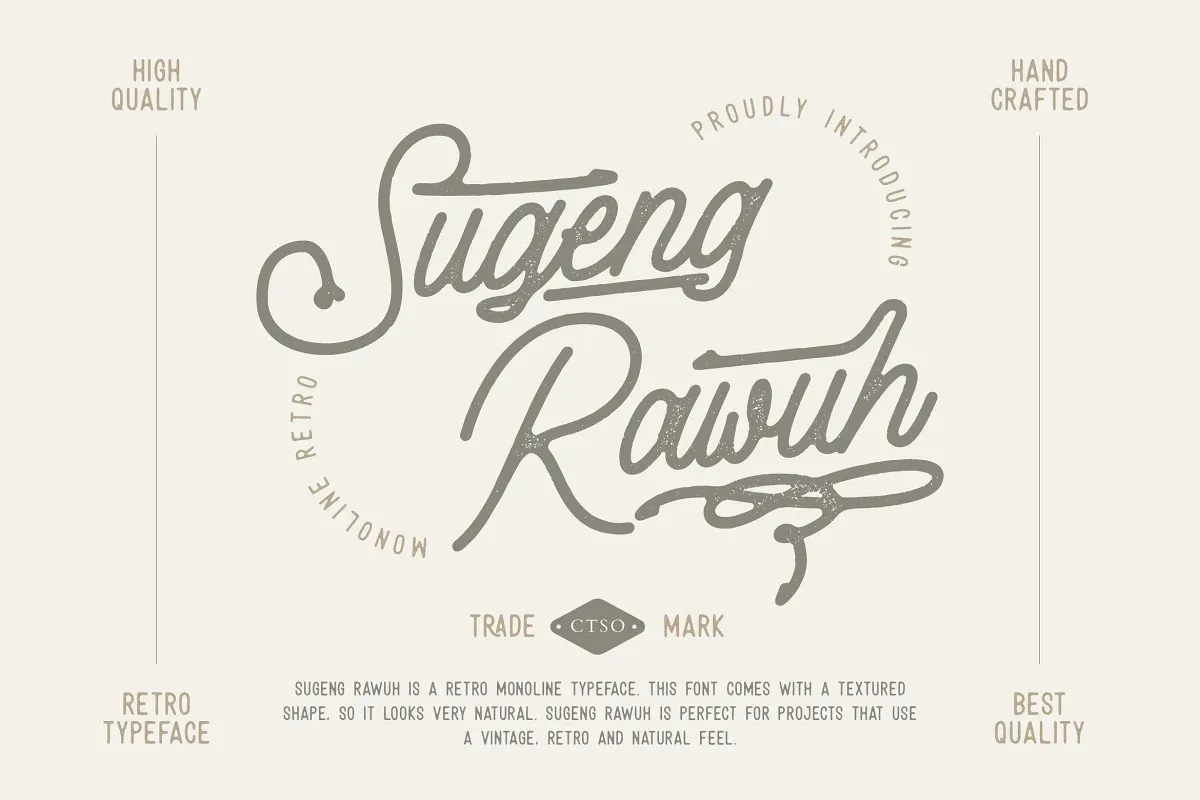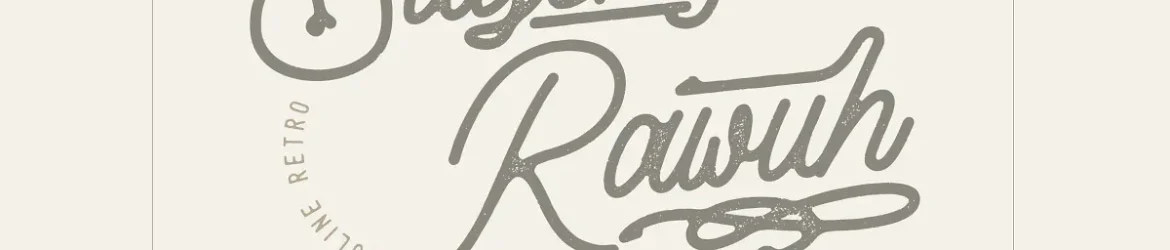
A Sugeng Rawuh Font é uma escolha perfeita para quem busca dar um toque natural e vintage a seus projetos digitais. Desenvolvida pelo site 99designs, ela traz o charme de uma escrita à mão antiga com um toque refinado. Este script vem acompanhado de um formato texturizado que cria uma aparência muito natural, tornando-o ideal para aquelas iniciativas que buscam a sensação vintage e retro tanto quanto a primalidade da natureza. A Sugeng Rawuh é perfeita para personalizar sua marca ou criar layouts gráficos que se destacam, oferecendo um visual único e autêntico ao seu trabalho digital.